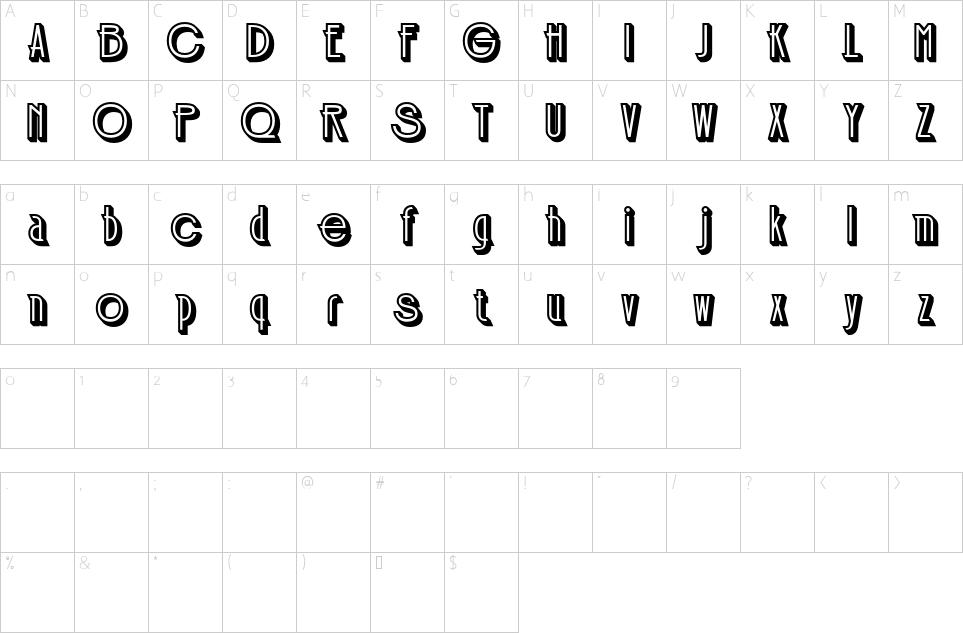
A fonte Jerio é uma opção incrivelmente elegante para designers e criadores de conteúdo. Ela foi projetada por Craft Supply Co e está disponível gratuitamente tanto para sistemas Windows quanto para Mac. Jerio é perfeita para criar uma mistura única de texto e imagens, destacando-se por seu design limpo e minimalista. Seu uso se estende a uma variedade de aplicações, desde design gráfico até criação de sites. Até o momento, a fonte Jerio foi baixada 106 vezes, demonstrando seu valor e popularidade entre os criadores de conteúdo. Seja para expressar ideias de uma maneira clara ou criar um efeito visual atraente, Jerio é um recurso indispensável para seu portfólio de ferramentas digitais.